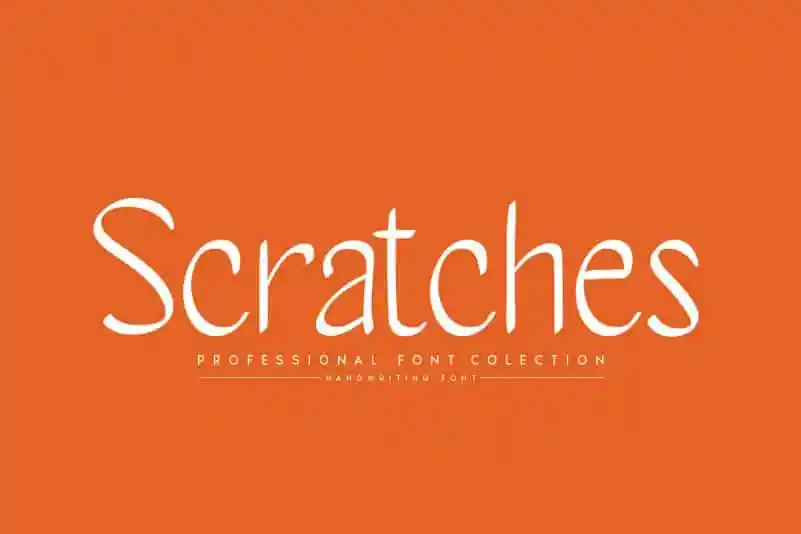
Scratches Script Font – Download Grátis
A fonte ‘Scratches Script Font’ é uma elegante fonte desenhada à mão, com um estilo naturalmente suave e amigável que se destaca por sua versatilidade. Suas linhas fluidas e personalizadas fazem dela a escolha perfeita para criar designs diversos, desde selos e cartões de aniversário até logos e letras de música. O designer andikastudio criou uma fonte única que não apenas destaca seu talento no campo da desenho à mão, mas também oferece inúmeras possibilidades para quem a usa. Seu único limite é o seu próprio pensamento criativo – ‘Scratches Script Font’ permite que você use sua imaginação de forma impressionante em uma variedade de projetos. Compreender a riqueza e diversidade da fonte, é um passo à frente na jornada de criação de qualquer designer ou artista.